Web开发者应该关注的技术及常见网页字体介绍
网页设计中常用的字体
字体在网站中扮演了相对重要的一个角色,所以在网站中,选用什么样的字体也是一个相对比较重要的工作。今天跟大家分享下在网站当中常用的字体。都知道,字体主要分为称线字和无称线字。其实细分的话还有等宽字体、梦幻字体和花体字。但今天我们主要针对常用的称线字和非称线字来讲。
称线字和非称线字的区别可以看下图:
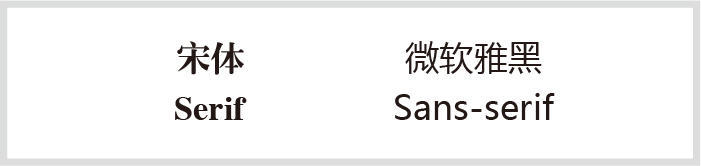
可以看到左边的中文和英文字属于称线字,右边中文和英文属于非称线字。称线字指的是在字的笔画开始、结束的地方有额外的装饰,而且笔画的粗细会有所不同。比如我们常用的宋体,观察比划可以看到横细竖粗的特点,这就是典型的称线字。非称线字也叫无称线字,无衬线字体没有这些额外的装饰,而且笔画的粗细差不多。比如微软雅黑。
称线字体容易识别,它强调了每个字母笔画的开始和结束,因此易读性比较高,非称线字则比较醒目。所以,在使用的过程中需要根据网站的定位而选择相应的字体。
下面简单给大家介绍网页中常用的几种字体:
1、微软雅黑
Vista之后新引入的字体,这个字体的使用率不用说了,可以说是web里面最安全的一个字体。字体方正、简洁,被广泛使用。整体比较简洁。
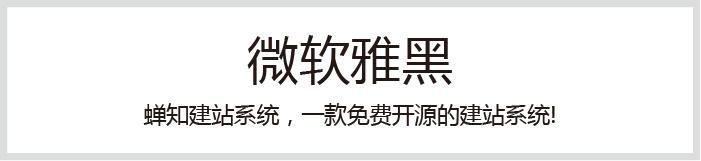
2、黑体
黑体字和微软雅黑差不多,作为非称线字中的一种,一样具备方正、简洁、醒目的特点。这样的字体特别适合当标题。其实黑体在使用上没有微软雅黑来得清晰明亮,一般在微软雅黑和黑体的选择下,个人更倾向微软雅黑。字体简洁醒目。
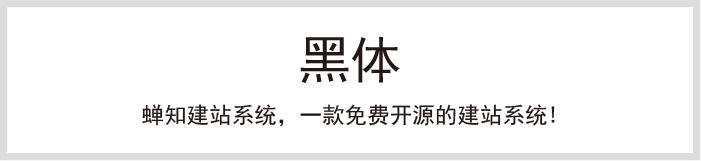
3、华文细黑
华文细黑是Mac下的默认中文,这套字体跟前面的微软雅黑相比较,更显绢细、秀气。笔划细节比微软雅黑处理的多一些,所以整体给人比较精致的感觉。注意一下,华文细黑并不是所有电脑的自带字体,当网站文字用到这个字体的时候,是需要在自己电脑上下载这套字体的。在写css代码的时候,font-family应该设置的选择性多一下,以保证界面打开的最佳效果。
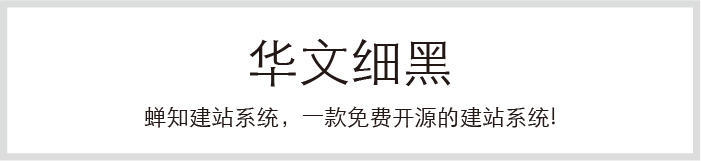
这个字体就不给大家做展示效果了,因为这个不是系统的默认字体,电脑上没有安装这个字体的也看不到网页的原始效果。
4、中易宋体
前面介绍的三款字体都是非称线字,接着要介绍的是称线字体——中易宋体,简称宋体。宋体在我们的日常中使用范围也很广,这是电脑自带的其中一种字体。宋体是为适应印刷术而出现的一种汉字字体。笔划有粗细变化,常用于书籍、杂志、报纸印刷的正文排版,所以在大篇幅文章的设计时,可以采用宋体。这个字体是Windows系统下最常见的字体,小字体点阵,大字体TrueType。大标题显示时字体不是很好看,所以一般不建议用宋体来当标题。
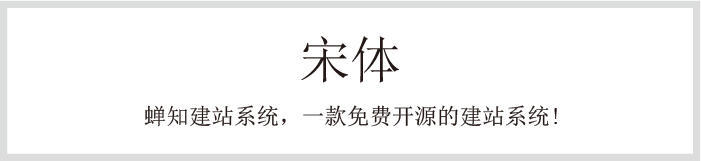
这种字体的选择一般出现在一些个性比较强的网站中,传统、专业、公正、官方、权威,宋体就表现了这种特点。
5、 Arial
说到Arial,这套字体是微软公司网页核心字体之一,最常用的sans serif字体,当字号很小时不容易阅读。但是,大写的“I”和小写的“l”是无法区别的,所以一般可以考虑用Tahoma字体来替代。这套字体方正、不花巧、方便阅读和印刷清晰。使用范围也是特别的广泛。但是要知道的是,苹果系统下是没有这套字体的,苹果系统下默认的是Helvetica。
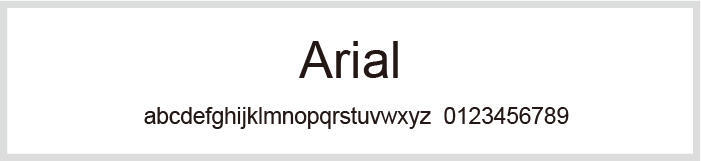
禅道项目管理软件的英文网站,幻灯片采用的字体就是Arial,可以看下这套字体在幻灯片下粗细的组合形态。
6、Tahoma
Tahoma是英文Windows操作系统的默认字体,这个字体比较均衡,是种非常圆滑的字体。这个字体和中文混排显示时,不会出现中英文不对齐的状态。这套字体解决了Arial大写“I”与小写“l”难以分辨的问题。也相当于在Arial上优化了不少。除此,细看这套字体,可以发现其实在一些笔划的处理上还是很精致的。
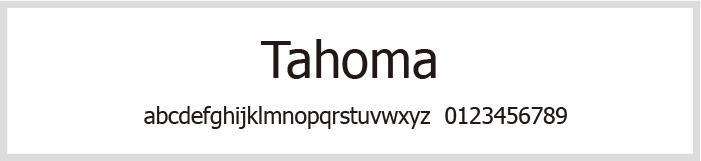
zui前端框架网站,英文字体的设置上也用到了这个字体,虽然不是第一优先选择,但是可以看出Tahoma这套字体的使用率也是很高的。
7、Helvetica
说到Helvetica这套字体,应该是设计师们的最爱了吧。这套字体属于 Realist风格,拥有简洁现代的线条,受到大部分设计师的追捧。这种字体给人一种简单、现代化、休闲轻松的感觉。适用于扁平化设计,也适合搭配任何设计项目,包括banner、平面设计以及网页字体等。在Mac下面被认为是最佳的网页字体,但在Windows下由于Hinting的原因显示很糟糕。
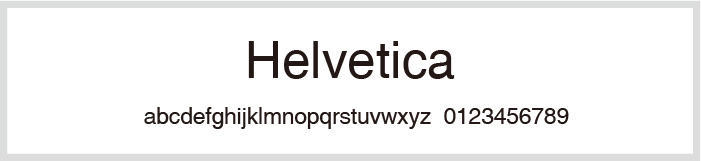
8、Georgia
说到英文的称线字,肯定首选是Georgia。这套字体笔划粗重,衬线明线,轮廓较大,小字体显示也很清晰,同时细节还不错。此种字体风格优雅又精致,可用于电影海报、游戏、时尚类网页设计中。
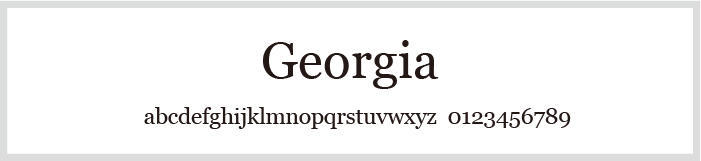
林肯的官网,Georgia是官网的第二优先选择显示的字体。网站比较现代,在一些幻灯片当中结合了Georgia字体,称线字和非称线字的相结合,可以使得整个网站更生动。
在专业的网页设计里,除了Banner图、广告语等特殊情况可能会用到特殊字体,网页中使用的字体以不超过2种为准,并且最好采用标准字体,比如中文的宋体、微软雅黑,英文的Arial、Helvetica。只有使用这些系统自带的字体,才能让前端开发人员在排版时高程度地还原设计稿的文字效果。倘若使用了特殊字体,在设计font-family的时候,应该多设置几种字体的优先顺序,以确保网页显示的最佳效果。当然,我们一般情况下建议使用系统自带的字体。
面向程序员的开源字体集
在百花齐放的开源世界中,开源字体属于较为小众的一个分支。不过往往越是小众的领域,反而会诞生出更多惊艳的作品。本文将为大家介绍开源字体中或颇具特色,或制作精美,或独具匠心,或有深厚历史背景的作品。
JetBrains Mono
开发商:JetBrains
JetBrains Mono 是 JetBrains 公司专门为开发者打造的编程字体——甚至有「最漂亮的编程字体」之称。
这款字体充分考虑了长时间查阅代码可能导致的眼睛疲劳问题,以及与之相关的因素,比如字母的大小和形状、字形之间的空间量、自然等宽平衡、不必要的细节、以及难以区分的符号或字母(l 和 I)和连字等。
JetBrains Mono 提供了 Thin、ExtraLight、Light、Regular、Medium、SemiBold、Bold 和 ExtraBold 共 8 种字体粗细,包含英文数字字符和西文字体,支持 147 种语言,但不包含中文,默认情况下中文会显示为系统的默认中文字体。
JetBrains Mono 字体展示效果
Cascadia Code
开发商:微软
Cascadia Code 是微软打造的一款等宽编程字体。这款字体的字形风格特别,它除了优化代码的可读性、让字母数字和符号更易辨认之外,最大的特点是支持编程连字 (Programming Ligatures),即在输入的时候,可以通过组合字符来创建新的字形。
Cascadia Code 字体展示效果
Source Code Pro
开发商:Adobe
Source Code Pro 是 Adobe 打造的等宽编程字体,非常适合用于编程场景,支持 Linux、macOS 和 Windows 等操作系统,提供了 ExtraLight、Light、Regular、Medium、Semibold、Bold 和 Black 共 7 种字体粗细。
Source Code Pro 采用了开源字体许可证 SIL Open Font License,开源免费且可商用。
Source Code Pro 字体展示效果
Fira Code
许可证:SIL Open Font License 1.1
Fira Code 是专为程序员打造的编程字体,除了具有等宽等基本属性外,还加入了编程连字特性 (ligatures)。
作为一种编程字体,Fira Code 对 ASCII/框绘图、电力线和其他形式的控制台 UI 具有出色的支持:
Fira Code 是第一个提供专用字形来渲染进度条的编程字体:
Fira Code 采用了开源字体许可证 SIL Open Font License,开源免费且可商用。
本文虽然是面向程序员的开源字体盘点,但不会仅限于“编程”这一用途,下面将要介绍的字体或极具创意,或制作精良,或充满传统文化特色。
齐伋字体
许可证:SIL Open Font License 1.1
齐伋体 (QIJI Font) 是提取自明代木版印刷书籍(凌闵刻本)的字体,亦称作「令东齐伋体」。
齐伋体笔画风格书法特征浓郁,比常规的明朝体更具韵律感,富有人文气息,非常适宜用于需要展现人文感、手作感、古拙感的场景。这款字体基于思源宋体改造而来,对中文汉字支持极佳。
齐伋体展示效果
霞鹜文楷(LXGW WenKai)
许可证:SIL Open Font License 1.1
霞鹜文楷是一款开源中文字体,名字取自于王勃的《滕王阁序》——“落霞与孤鹜齐飞,秋水共长天一色”。
霞鹜文楷衍生自开源字体 Klee One,后者是一款日文的教科书字体,由日本著名字体厂商 FONTWORKS打造,兼有仿宋和楷体的特点。霞鹜文楷基于 Klee One 补全了简繁常用字。
霞鹜文楷展示效果
铁蒺藜体
许可证:SIL Open Font License 1.1
铁蒺藜体是一款造型尖锐的开源中文美术字体,基于 Fontworks 出品的日文字体 Reggae One 扩充、调整字形,并添加 OpenType 特性,以满足简体中文的使用需求。
铁蒺藜体展示效果
麦当劳薯条字体
顾名思义,这是一款以麦当劳薯条为灵感而创作的字体,采用薯条和番茄酱作为构建元素,极具创意且有特色。
麦当劳薯条字体展示效果
兼容情况
支持的软件和操作系统:Illustrator CC 2018 以上 / Photoshop CC 2017 以上 / InDesign CC 2019 以上 / QuarkXPress 2018 Pages(macOS) / Keynote(macOS) / Sketch(macOS) / Paint.NET(Windows)
支持的浏览器:Chrome / Safari / Firefox (26+) / Microsoft Edge (38+, Win 10)
目前此款字体已免费开放下载,只需标注 #麦当劳薯条体 即可自由使用,包括商业用途。
最后,提到开源字体有两个重量级作品是无法绕开的——「思源黑体」和「思源宋体」。正是它们的珠玉在前,才得以诞生了更多优秀的派生字体。
思源黑体
许可证:SIL Open Font License 1.1
开发商:Google & Adobe
思源黑体(也称作 Source Han Sans 或 Noto Sans CJK)是 Google 和 Adobe 合作打造的开源字体,采用了开源字体许可证 SIL Open Font License,免费且可商用。“思源”二字取自于成语“饮水思源”。
思源黑体支持简体中文、繁体中文、日文、韩文以及英文;提供了 ExtraLight、Light、Normal、Regular、Medium、Bold 和 Heavy 共 7 种字体粗细,可以满足不同场景下的文字显示需求。适合设计师、开发者,以及普通用户使用。
思源黑体展示效果
思源宋体
许可证:SIL Open Font License 1.1
开发商:Google & Adobe
继“思源黑体”后,Adobe 和 Google 再度联手创造了“思源宋体”(称作 Source Han Serif 或 Noto Serif CJK)。思源宋体也采用了开源字体许可证 SIL Open Font License,免费且可商用。
思源宋体同样包含简繁中文以及日韩四种汉字写法和 ExtraLight、Light、Regular,Medium、SemiBold、Bold 和 Black 七种粗细字重,每种粗细字重分别收录了 65535 个字形,七种字重共收录高达 458745 个字形,可以满足不同的设计需求。
思源宋体展示效果
建议 Web 字体样式
通常用户看到的页面的样式 (css) 会受到三层控制:
第一层是浏览器的默认样式;
第二层是网页定义样式;
第三层是用户自定义样式.
和 CSS 一样,后面的优先级高于前面的,也就是说网页定义样式可以覆盖浏览器的默认样式,而用户自定义样式优先级最高。实际情况是虽然浏览器都或多或少提供了用户自定义样式的功能,但是极少数会有用户去自定义,一般用也是高级用户。而浏览器默认的样式往往在不同的浏览器、不同的语言版本甚至不同的系统版本都有不同的设置,这就导致如果直接利用默认样式的页面在各个浏览器下显示非常不一致,于是就有了类似 YUI 的 reset 之类用来尽量重写浏览器的默认设置保证各个浏览器样式一致性的做法。
拿字体来说,各个浏览器默认的字体种类、字体大小和字体行高都不一样,比如 IE8 的中文版在 Windows XP 下显示网页时默认字体是宋体,而英文版肯定不会如此。所以需要统一设置默认的字体样式,以便实现一致的显示效果来保证设计的一致性和提高开发效率。
以后准备使用如下默认字体样式:
body{
font: 12px/1.5 arial;
}
字体:arial
页面的绝大部分内容字符都是中文, 毫无疑问目前为止在网页上最常用也是最通用的显示中文的字体是宋体,但是宋体在显示英文、数字和英文符号时过于糟糕,比如?字符,所以一般期望通过 CSS 来实现用更好的字体样式来显示它们,然后用宋体来显示中文和中文符号。之所以选择 arial 是因为:
1.Windows 和 Mac 都预装了这款字体,应该是使用最广泛的网页字体了。 它的潜在对手 tahoma 和 helvetica 就没有这么幸运了。
2.视觉设计的专业人士可能会认为在 Windows 中使用 tahoma、在 Mac 中使用 helvetica 更好, 比如淘宝的默认字体样式是 font: 12px/1 Tahoma, Helvetica, Arial, "\5b8b\4f53", sans-serif; 这是一个很不错的选择,但是你也会发现 Google、YAHOO、Youtube、Bing 甚至 MSN 的新版都 使用 arial 作为第一默认字体。 所以从美观和可读性上来讲 arial 应该是完全可以接受的。
3.一般情况下设置 font-family 都会在最后设置通用字体族以保证其安全性, 比如 Google 的设置为 font-family:arial,sans-serif; 但是至少在非中文版的 Win7 下当编码是 GBK 时,IE8 会因 sans-serif 来渲染宋体, 导致字体出现变形,这就是为什么淘宝需要在 sans-serif 前加上宋体而 Google 无需这样做的原因。
4.因为中文字体的选择非常有限,所以目前所有的主流浏览器都设置使用宋体来显示中文。 Baidu 的首页和搜索结果页使用 font-family:arial; 可以从侧面说明这样做的安全性。 可能有人注意到 Firefox 中国版默认显示的中文字体是微软雅黑, 这是因为谋智网络擅自修改了用户自定义样式,不允许网页的样式覆盖浏览器设置的样式。 也是由于类似的情况,我们要弹性设计网页非常重要。
使用英文字体作为第一默认字体会导致的问题之一就是中英文以及符号混排时的对齐问题、 通过设置行高和 hasLayout 能解决绝大部分情况,但是都不会很完美, 如果把字体改成 “宋体” 能彻底的解决问题。很明显,这个问题只出现在 IE 上。 所以,如果你的网站很少使用英文、数字和英文符号, 那么直接设置 {font-family:\5b8b\4f53;} 也是很合理的选择。
大小:12px
12px 是宋体能显示的极限,虽然微软雅黑能显示更小的字体,但目前的应用环境尚未成熟。 由于宋体基本上是目前显示中文唯一的通用 Web 字体,所以 12px 成为最常用的字体大小。 我们当然可以依据产品的需要来修改这个默认值。不用考虑基于字体大小(em)的设计。在 Chrome3.0 之后的中文版中,字体大小最小值是 12px,比如你设置最小字体为 10px,最后也变成 12px。
行高:1.5 倍
这是一个经验值,不同的产品对这个值要求可能不同,但我们一般会设置最常用的为默认值.
比如 YUI 的 font 中是 font:13px/1.231 arial,helvetica,clean,sans-serif; 即字体大小默认值是 13px,行高是 13*1.231=16.003px,默认的行高是默认字体的 1.231 倍。 对于中文来说,常用的字体大小 12px、14px、16px、18px 等偶数大小, 在 IE6 和 IE7 设置其行高也为偶数能解决一些特殊情况下的字体对其问题。
在 IE6 和 IE7 中,行高值必须大于字体的 2px 才能保证字体的完整显示或当其作为链接时能有效显示下划线。
设置 line-height 时,注意不要使用单位(包括 % 在内), 因为子节点会继承经过运算后的 line-height 值, 所以当使用单位后浏览器会把 line-height 计算成第一次定义的绝对值, 而不会随着字体大小的变化而变化,而无单位的数值表示是所在容器的 font-size 的倍数, 所以设置为无单位的数值是最佳选择。
深入 CSS 行高非常有利于理解 line-height,值得一读。
性能和效率
大部分平台都有 arial,减少浏览器的查找时间。
代码最少,书写方便。arial 基本上是名字最短的字体了,可以节约 CSS 的大小。
所有的字母都小写,目前 Google 就是这样做的,好处是既可以编写更快也能提升 Gzip 压缩的效率。
中文最好用 unicode 表示,比如使用宋体是 {font-family:\5b8b\4f53;},使用微软雅黑是 {font-family:\5fae\8f6f\96c5\9ed1;}, 这样的好处是避免编码问题,同时能得到所有的主流浏览器的支持。
使用正确的字体种类写法,避免使用引号,这样可以缩小 CSS 的大小。
中文字体可以按上一条方式来编写。
未来
通过对中英文及符号混排的测试发现微软雅黑其实表现相当不错,包括英文数字和英文字符以及在 IE6 和 IE7 的显示效果上,但唯一的遗憾是在 XP 下如果安装了微软雅黑字体的用户没有打开 “使用屏幕字体的边缘平滑” 选项的话,在 Firefox、Safari 和 Opera、特别是 IE6 下会非常模糊难以辨认。针对这个问题目前并没有很好的解决方案,所以只有等到 IE6 使用比率非常小的时候才可能正式的使用它。或许需要到 XP 退出的时候。
虽然很早就有了 @font-face,但是浏览器的支持、网速和商业问题,导致它很少被应用。关于字体的好消息是 Firefox3.6 将支持 Web Open Font Forma。关于 Web 字体未来的相关信息可以看 Web 字体的未来、关于 Web 字体: 现状与未来和再谈 Web 字体的现状与未来。